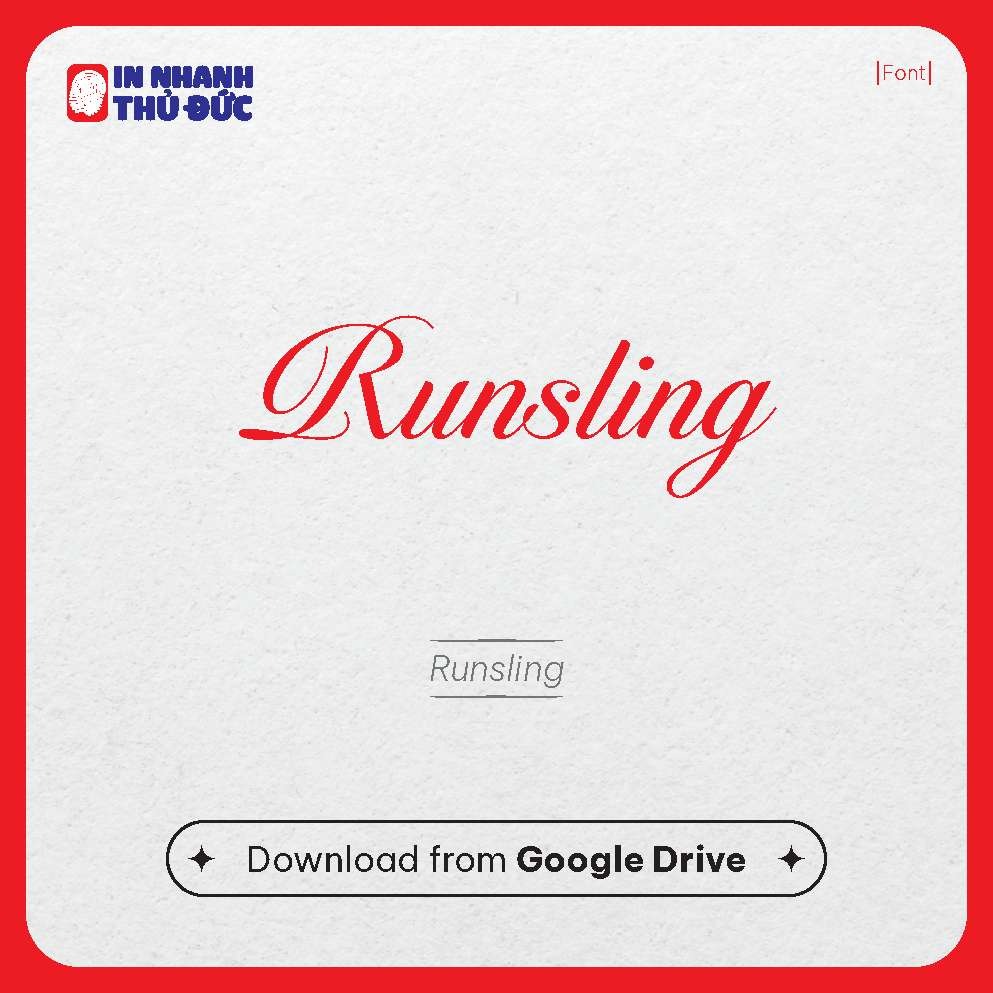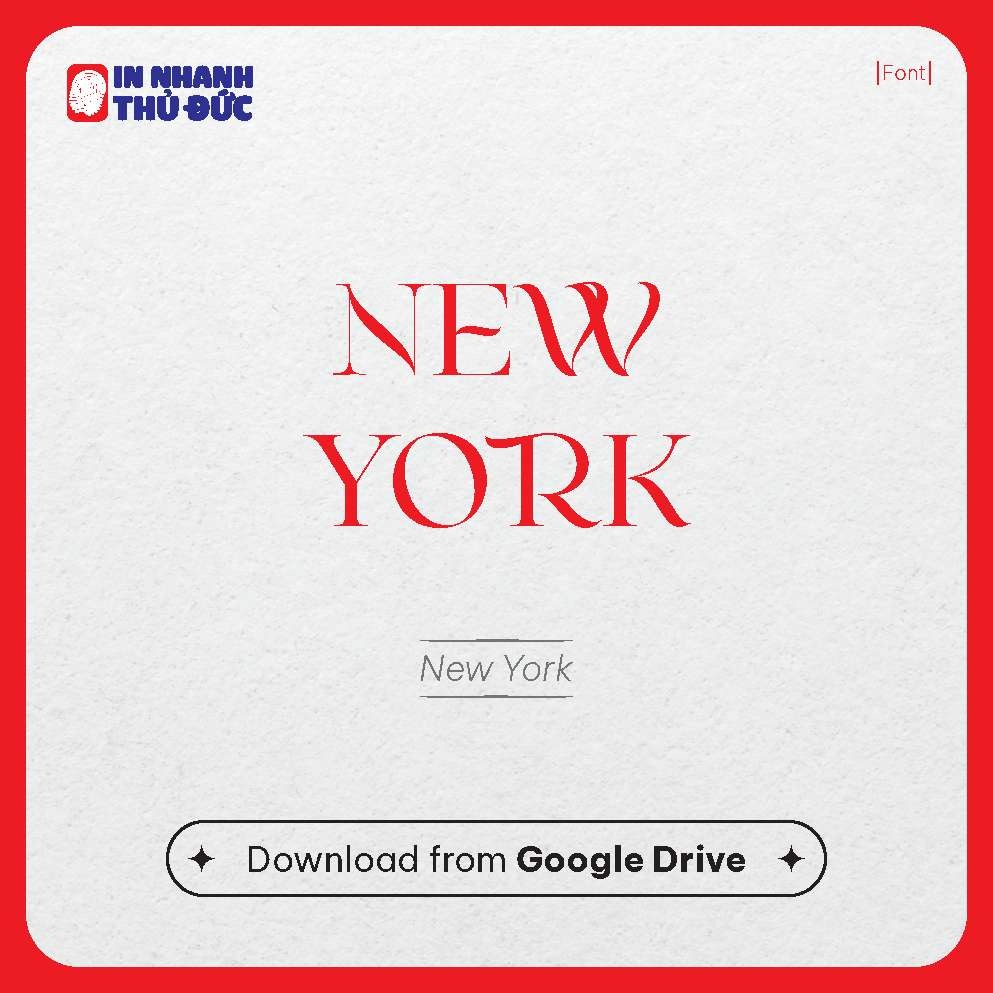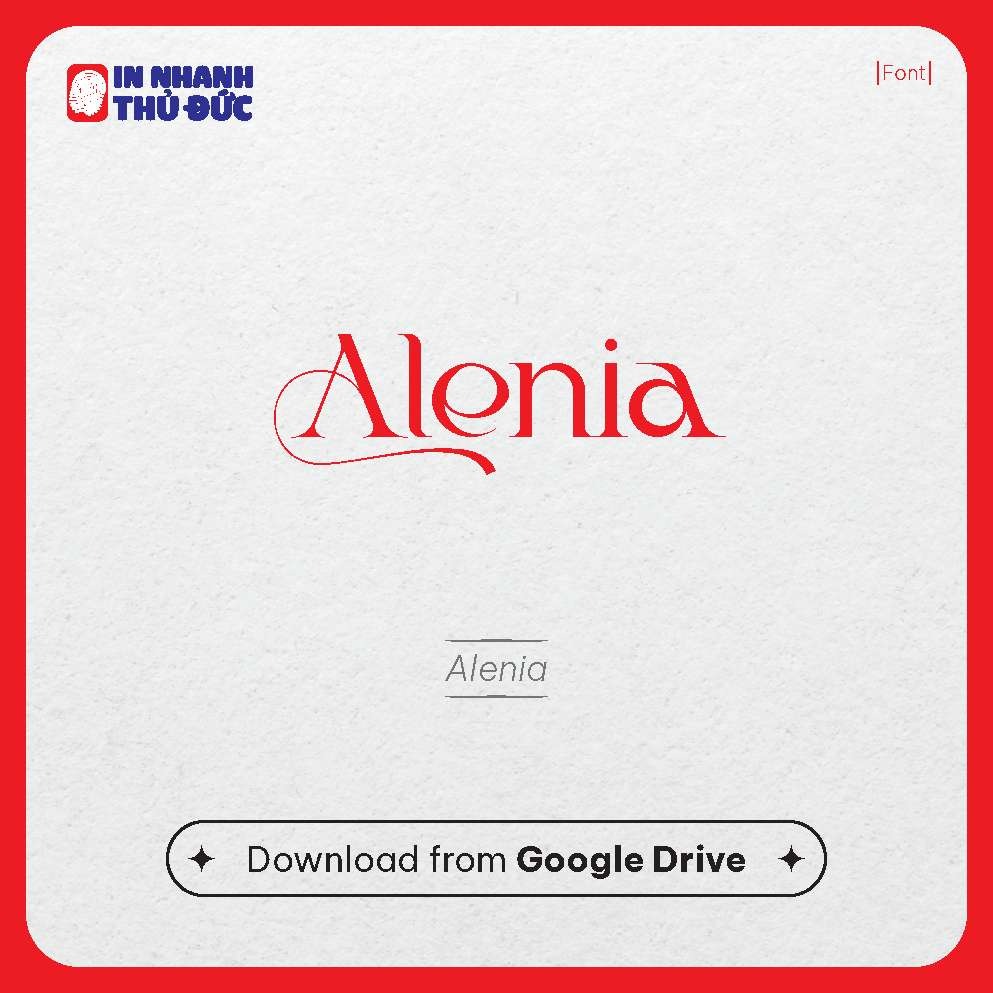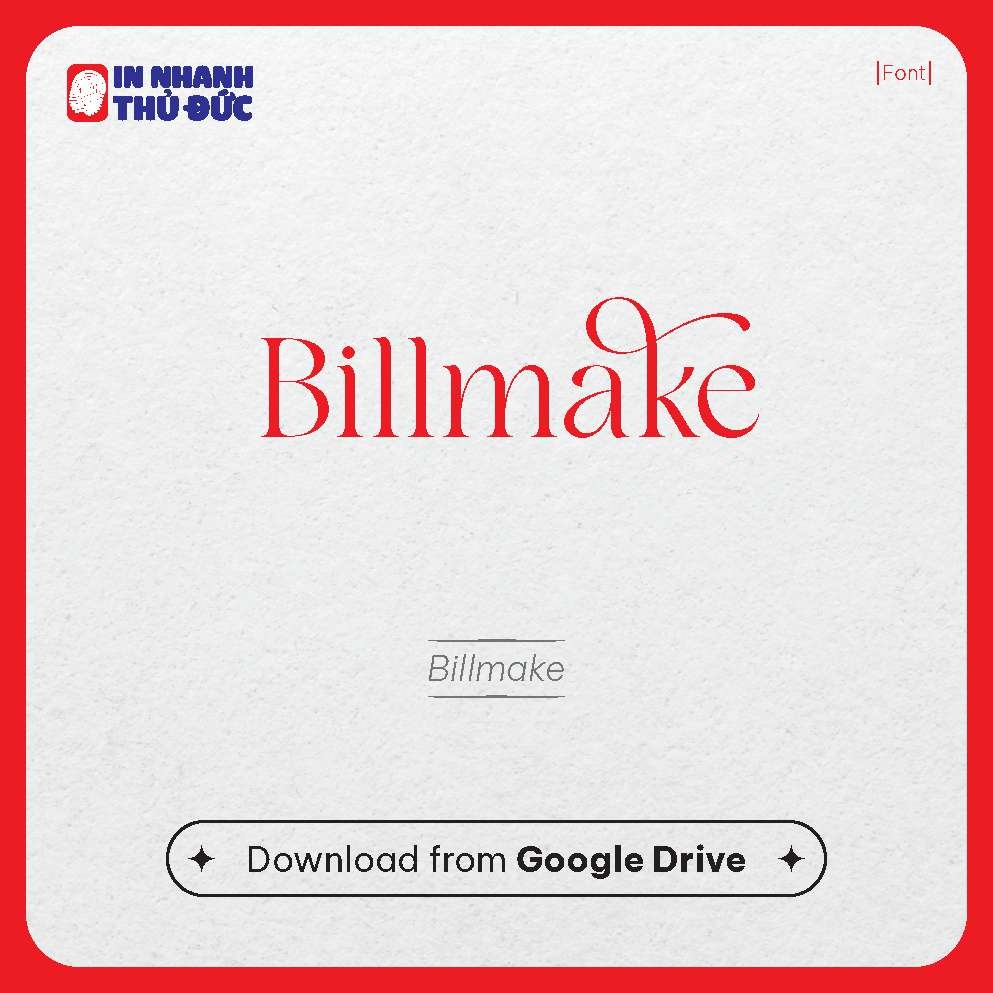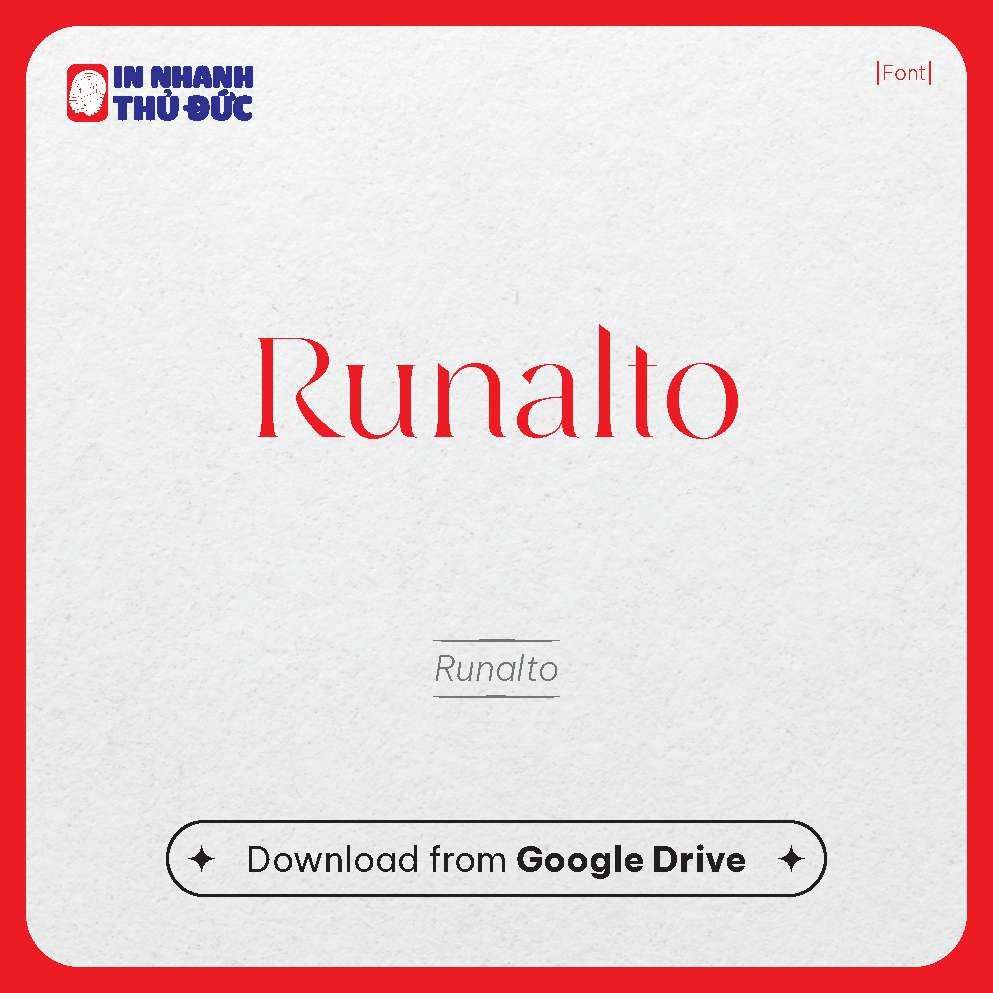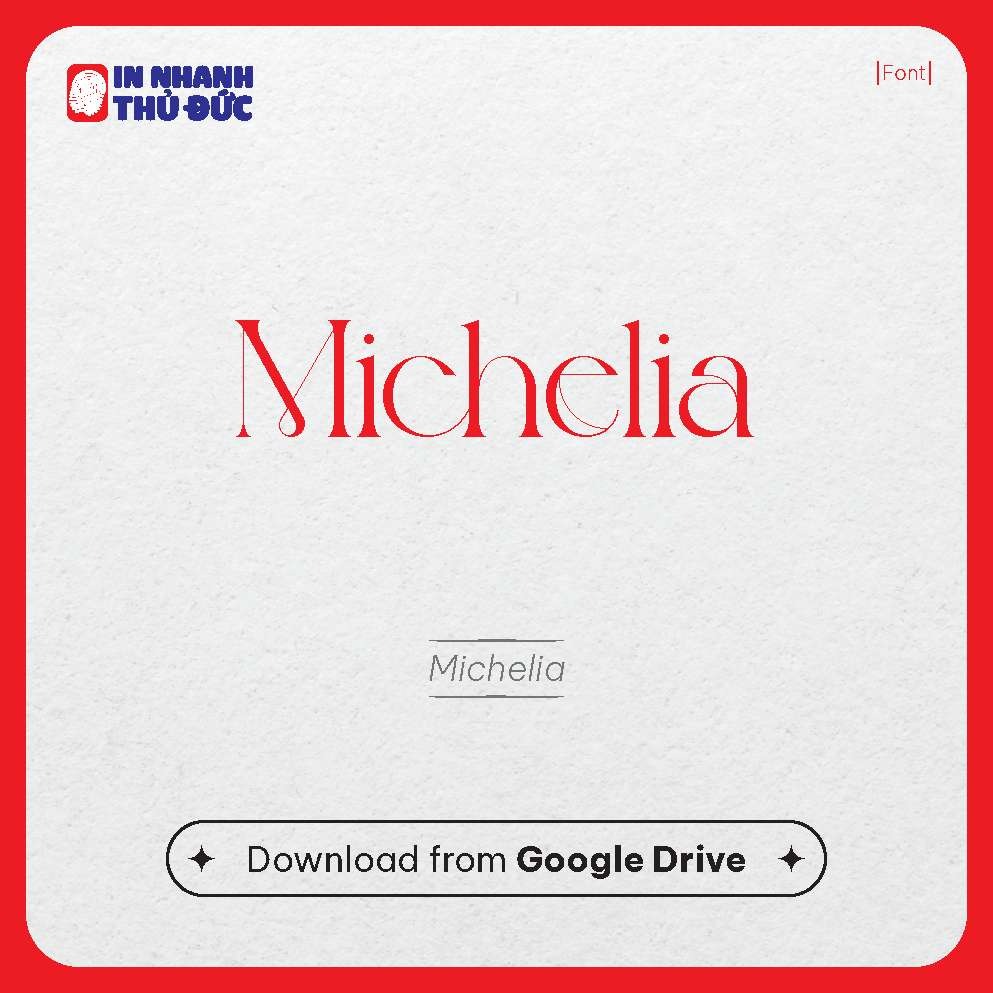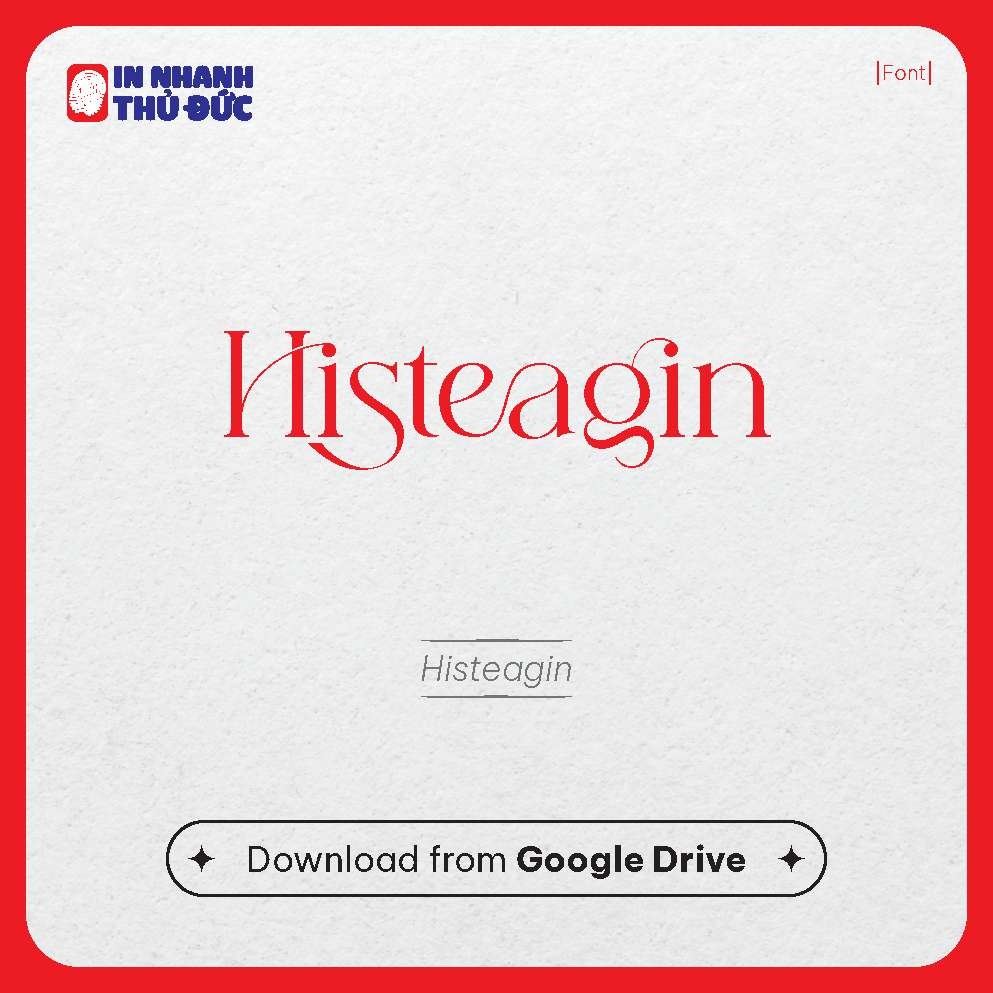
Khám Phá 7 Font Chữ Việt Hóa "Đỉnh Cao" Cho Ngành Làm Đẹp & Spa (Tuyển Chọn Từ In Nhanh Thủ Đức)
Hôm nay, hãy cùng "giải mã" bộ sưu tập 7 font chữ Việt hóa đẹp và độc đáo, được tuyển chọn kỹ lưỡng bởi In Nhanh Thủ Đức, dành riêng cho các doanh nghiệp trong lĩnh vực spa, thẩm mỹ viện, salon tóc, nail và các ngành nghề liên quan đến làm đẹp. Chúng ta sẽ đi sâu vào đặc điểm, cảm hứng và những ứng dụng lý tưởng của từng "ngôi sao" font chữ này.
Phần 1: Vì Sao Font Chữ Việt Hóa "Chuẩn Gu" Lại Là "Vũ Khí Bí Mật" Của Ngành Làm Đẹp?
Trước khi chiêm ngưỡng vẻ đẹp của từng font, hãy cùng khẳng định lại sức mạnh của typography trong ngành này:
- Định Hình Bản Sắc Thương Hiệu: Font chữ là tiếng nói không lời, giúp khách hàng nhận diện và ghi nhớ thương hiệu spa của bạn.
- Khơi Gợi Cảm Xúc Mong Muốn: Sự mềm mại, sang trọng, thư thái hay hiện đại, năng động? Font chữ phù hợp sẽ truyền tải đúng "mood" dịch vụ.
- Nâng Tầm Chuyên Nghiệp & Tin Cậy: Một thiết kế chỉn chu với font chữ đẹp, dễ đọc, hỗ trợ đầy đủ tiếng Việt sẽ tạo dựng niềm tin nơi khách hàng.
- Tăng Sức Hút Cho Mọi Điểm Chạm: Từ logo, website, menu dịch vụ, đến các bài đăng quảng cáo, font chữ đóng góp vào sự thành công của tổng thể thiết kế.
Phần 2: "Diện Kiến" 7 "Ngôi Sao" Font Chữ Việt Hóa Từ Bộ Sưu Tập Đặc Biệt Của In Nhanh Thủ Đức
Đây là những "ứng cử viên" sáng giá, được Việt hóa chỉn chu, sẵn sàng đồng hành cùng thương hiệu làm đẹp của bạn:
2.1. Runsling – Nét Script Mềm Mại & Quyến Rũ
- Đặc điểm nổi bật: Runsling là một font Script (viết tay) với những đường nét thanh thoát, uyển chuyển và có độ kết nối cao giữa các con chữ. Nét chữ có sự thay đổi độ dày tinh tế, tạo cảm giác vừa cổ điển vừa hiện đại.
- Phong cách & Cảm hứng: Toát lên vẻ đẹp sang trọng, lãng mạn và đầy nữ tính. Runsling gợi nhớ đến sự chăm sóc tỉ mỉ, dịch vụ cao cấp và không gian thư giãn tuyệt đối.
- Ứng dụng lý tưởng:
- Tên thương hiệu spa, salon tóc, nail studio.
- Tagline, slogan bay bổng.
- Tiêu đề cho các liệu trình đặc biệt, gói dịch vụ cao cấp.
- Thiệp mời sự kiện, voucher quà tặng.
- Chữ ký thương hiệu trên các ấn phẩm.
- Lưu ý khi sử dụng: Do tính chất bay bướm, Runsling phù hợp nhất cho các dòng chữ ngắn, tiêu đề. Nên kết hợp với một font Sans-serif đơn giản cho phần nội dung để đảm bảo tính dễ đọc.
2.2. New York – Vẻ Đẹp Serif Hiện Đại & Thanh Lịch
- Đặc điểm nổi bật: New York là một font Serif (có chân) mang hơi hướng hiện đại, với các đường nét sắc sảo, chân chữ thanh mảnh và độ tương phản rõ ràng giữa nét dày và nét mỏng. Font chữ này thể hiện sự cân bằng giữa cổ điển và đương đại.
- Phong cách & Cảm hứng: Đem lại cảm giác sang trọng, tinh tế, chuyên nghiệp và có phần thời thượng, giống như chính thành phố mang tên nó.
- Ứng dụng lý tưởng:
- Logo thương hiệu mỹ phẩm cao cấp, clinic, spa y tế.
- Tiêu đề chính trên website, brochure, catalogue dịch vụ.
- Tên các dòng sản phẩm đặc trị.
- Thông tin liên hệ, địa chỉ cần sự trang trọng.
- Lưu ý khi sử dụng: New York khá đa năng, có thể dùng cho cả tiêu đề và những đoạn văn bản ngắn cần sự nhấn mạnh.
2.3. Alenia – Nét Cong Mềm Mại, Đầy Nghệ Thuật
- Đặc điểm nổi bật: Alenia có thể là một font Script hoặc một font Serif cách điệu với những đường cong mềm mại, độc đáo và mang tính nghệ thuật cao. Các chi tiết uốn lượn tạo điểm nhấn đặc biệt cho từng con chữ.
- Phong cách & Cảm hứng: Gợi lên sự dịu dàng, tinh xảo, một chút hoài cổ nhưng vẫn giữ được nét tươi mới. Phù hợp với các spa thiên về liệu pháp tự nhiên, thư giãn sâu.
- Ứng dụng lý tưởng:
- Tên thương hiệu spa boutique, các dòng sản phẩm hữu cơ.
- Thiết kế bao bì sản phẩm mang tính nghệ thuật.
- Tiêu đề các liệu pháp massage, chăm sóc da đặc biệt.
- Trang trí cho các ấn phẩm marketing cần sự bay bổng.
2.4. Billmake – Phá Cách Độc Đáo, Tạo Dấu Ấn Riêng
- Đặc điểm nổi bật: Billmake có thể là một font chữ mang tính Display hoặc Script với những nét phá cách, không theo một khuôn mẫu cố định. Có thể có sự kết hợp giữa các nét mạnh mẽ và những đường cong bất ngờ.
- Phong cách & Cảm hứng: Thể hiện sự sáng tạo, cá tính riêng biệt và một chút táo bạo. Phù hợp với các thương hiệu spa muốn tạo sự khác biệt, hướng đến đối tượng trẻ trung, năng động.
- Ứng dụng lý tưởng:
- Logo thương hiệu muốn gây ấn tượng mạnh.
- Tên các sự kiện, workshop độc đáo.
- Các chiến dịch quảng cáo cần sự nổi bật.
- Thiết kế cho các sản phẩm làm đẹp phiên bản giới hạn.
- Lưu ý khi sử dụng: Do tính độc đáo, nên sử dụng Billmake một cách có chọn lọc để tránh làm rối tổng thể thiết kế.
2.5. Runalto – Vẻ Đẹp Serif Cổ Điển, Vững Chãi
- Đặc điểm nổi bật: Runalto là một font Serif với cấu trúc vững chãi, chân chữ rõ ràng và độ tương phản cao giữa các nét. Mang trong mình vẻ đẹp cổ điển, sang trọng và có phần trang nghiêm.
- Phong cách & Cảm hứng: Tạo cảm giác tin cậy, chuyên nghiệp, chất lượng và sự trường tồn. Rất phù hợp với các spa, clinic có uy tín lâu năm hoặc muốn xây dựng hình ảnh đẳng cấp, đáng tin.